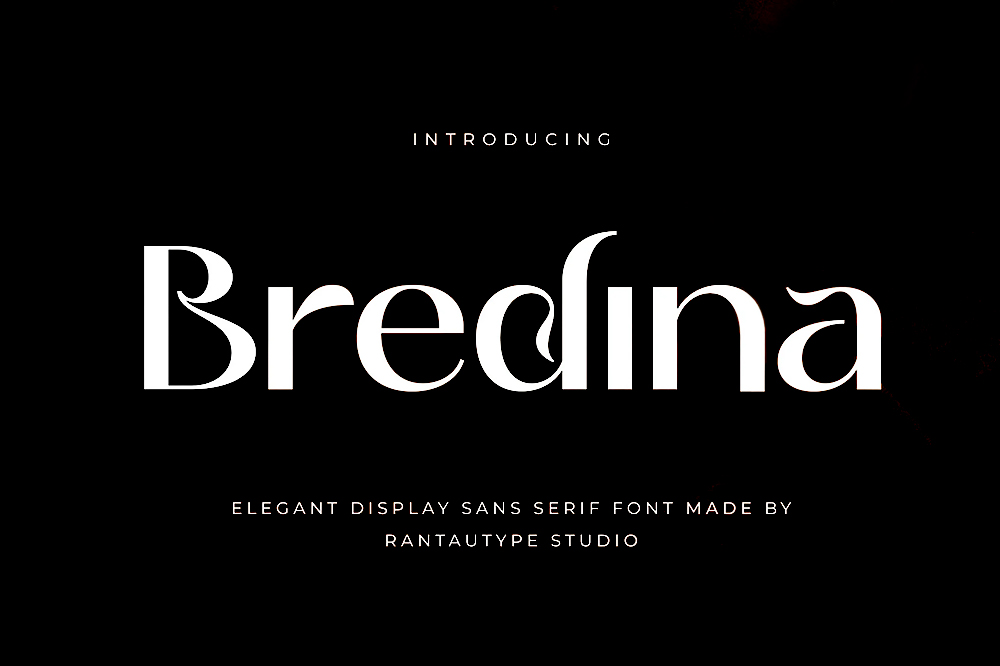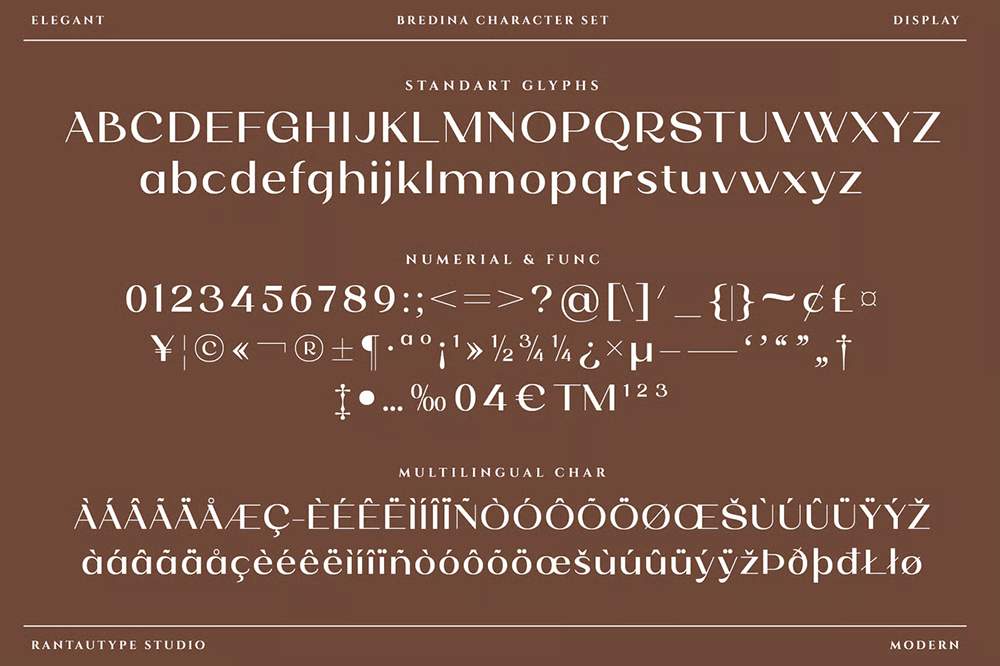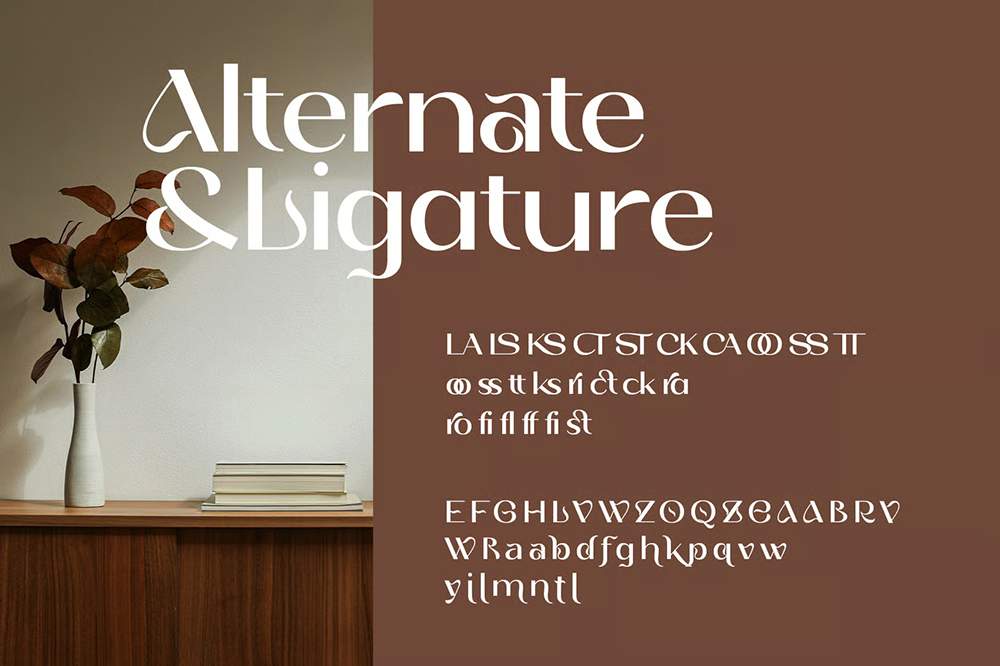
دانلود فونت انگلیسی Bredina Font
فونت پرمیوم و انگلیسی Bredina Font یک فونت جدید است و ظرافت و زنانگی را در بر میگیرد. Bredina انتخابی ایدهآل برای هرگونه تلاش خلاقانه، طراحی شیک…
فونت پرمیوم و انگلیسی Bredina Font یک فونت جدید است و ظرافت و زنانگی را در بر میگیرد. Bredina انتخابی ایدهآل برای هرگونه تلاش خلاقانه، طراحی شیک و سبک زندگی، مانند لوگو، تبلیغات، واترمارک روی عکسها، لوازم التحریر، پروژههای برندسازی، نمایشها و مجلات، دعوتنامهها، برندسازی شرکتی، طراحی محصول، برچسبها، پروژههای تجاری و بسیاری از پروژههای دیگر با ظاهری زیبا است.
مزایای استفاده از فونت لاتین Bredina چیست؟